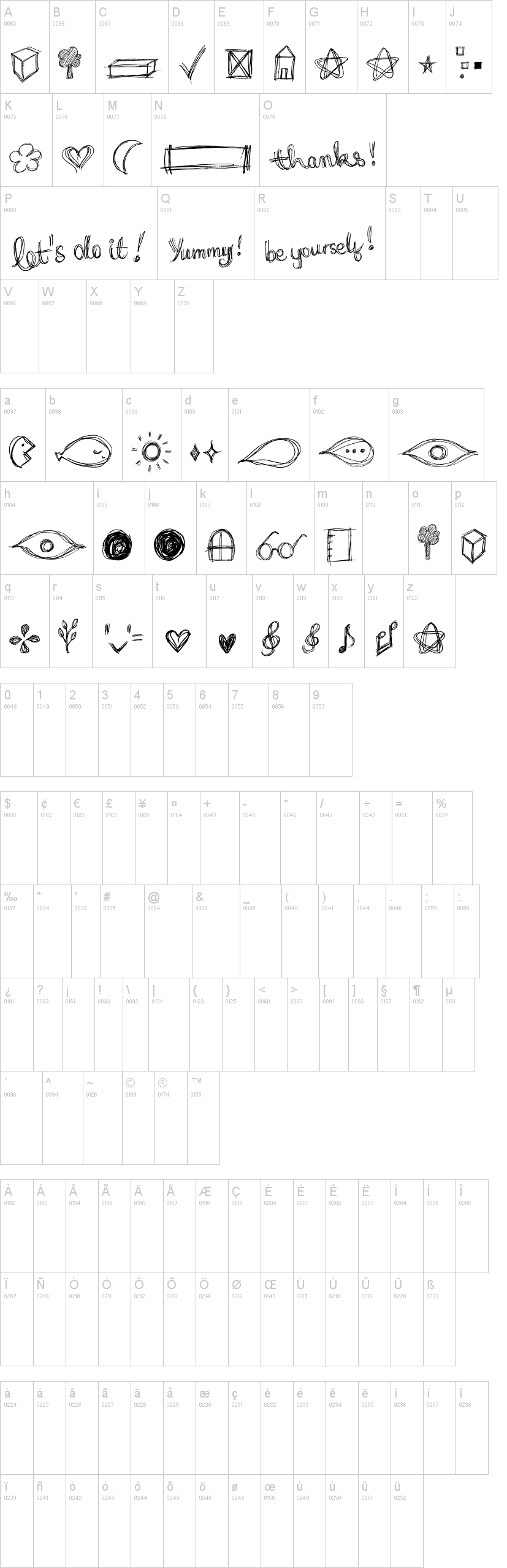
Go around the books - Symbols
Go around the books - Symbols 是一个字体,它的设计灵感来源于古籍中使用到的符号和图案。该字体的特点是线条简洁流畅,每个字符都具有独特的形式和风格。 Go around the books - Symbols 字体包含了许多常用的符号,例如箭头、星星、心形、圆形等等,同时也包含一些古代文化中使用的符号,例如卜卦、太极图案等等。 这个字体适用于许多不同的设计场景,例如印刷品、海报、标志、包装设计等等。它的简洁而独特的风格可以帮助设计师打造出独特的视觉风格,从而吸引观众的注意力。
Go around the books - Symbols是一款非常不错的手写艺术字体,具有很好的视觉感,适合于文化类的宣传设计、商业类品牌的广告和产品包装设计以及个性化文字排版等较多场景。